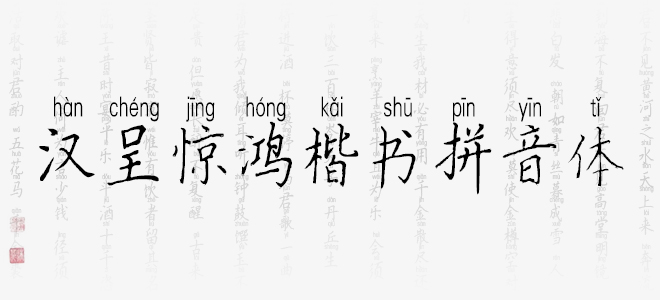
漢呈驚鴻楷書拼音體是漢呈字庫中一款自帶中文拼音標(biāo)注效果的楷書字體,字體線條粗細(xì)適中,筆畫隨性,結(jié)構(gòu)灑脫自在,具有很好的視覺感,適合于文化類的宣傳設(shè)計、商業(yè)類品牌的廣告和產(chǎn)品包裝設(shè)計以及個性化文字排版等較多場景。
漢呈驚鴻楷書拼音體